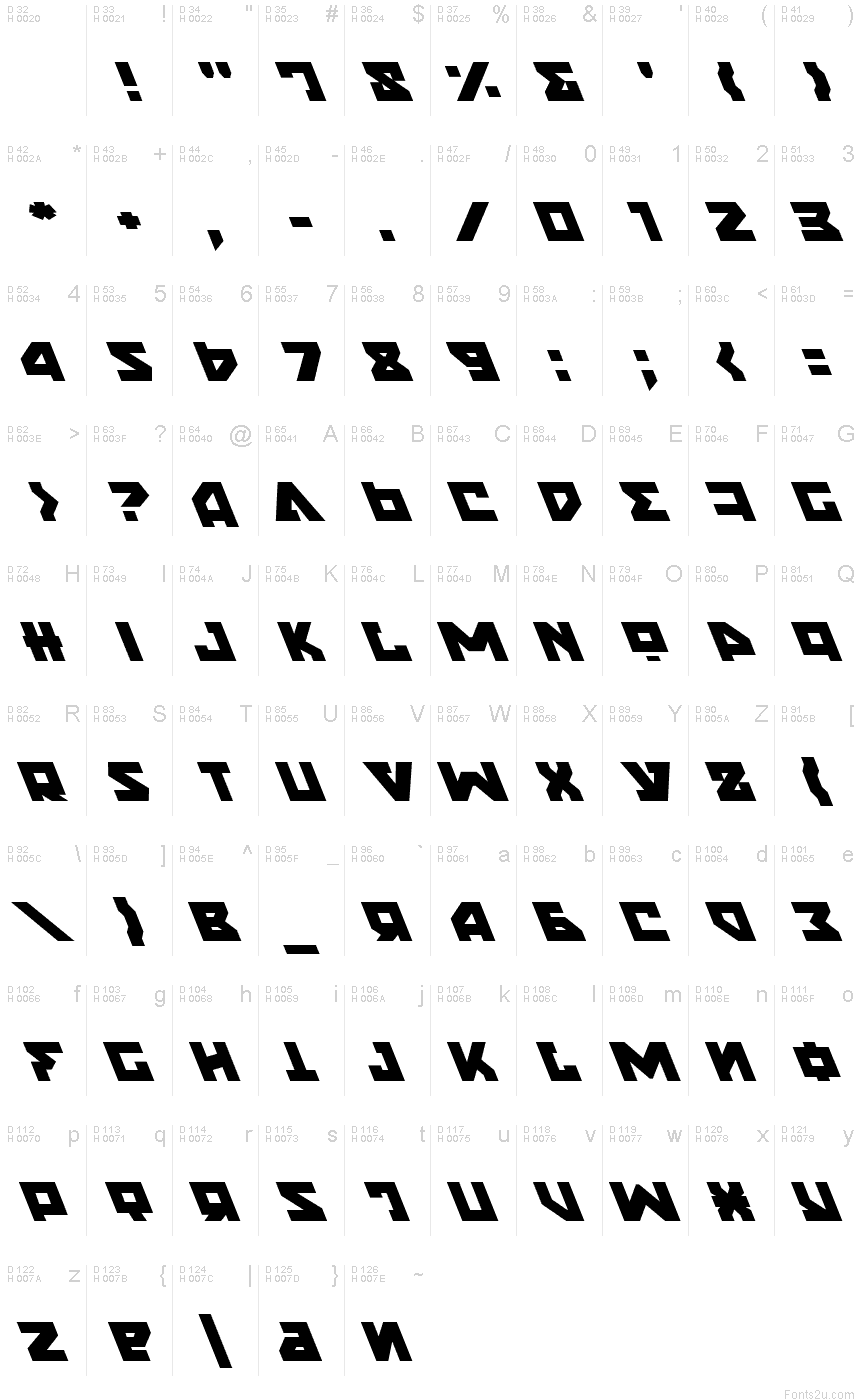
Nyet Leftalic od Iconian Fonts to darmowy, rosyjski krój typu display, oparty na ostrych, ukośnych cięciach i surowych, plakatowych sylwetkach. Pochyła konstrukcja nadaje literom napięcie w duchu propagandy, a powtarzające się kliny i ścięte rogi sprawiają, że styl bardziej kojarzy się z grafiką z epoki radzieckiej niż z generycznymi formami techno.
Ta wizualna siła świetnie sprawdza się w tytułach gier, plakatach imprezowych, okładkach albumów, gadżetach i etykietach piw, gdzie kanciasty rytm wykonuje większość pracy brandingowej. Krój ten świetnie wyostrzy też grafikę social mediową i opakowania, które mają przywoływać skojarzenia z blokiem wschodnim bez konieczności dodawania ilustracji.
Nyet Leftalic